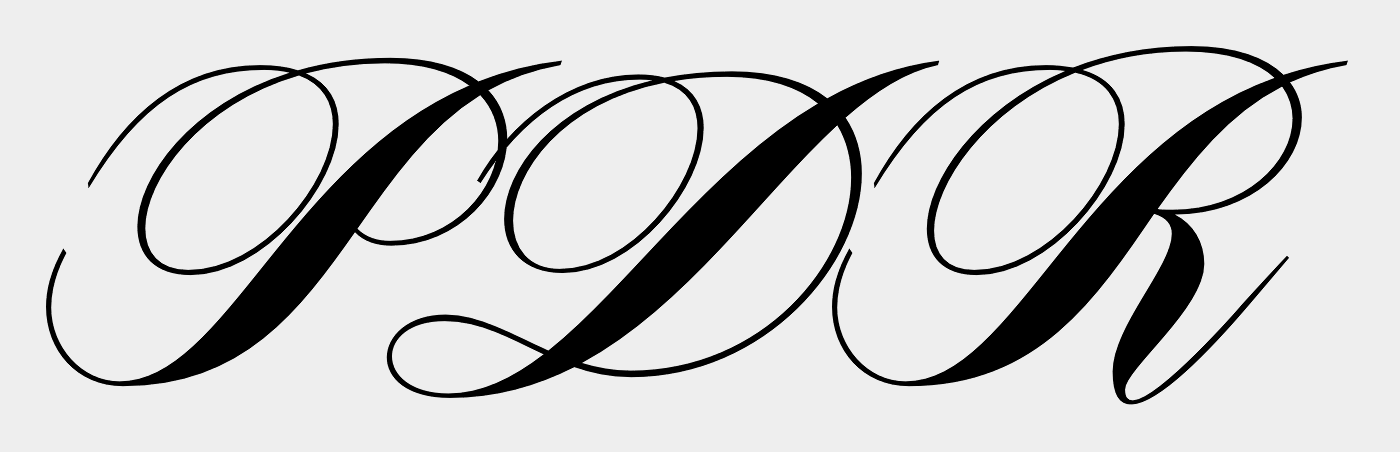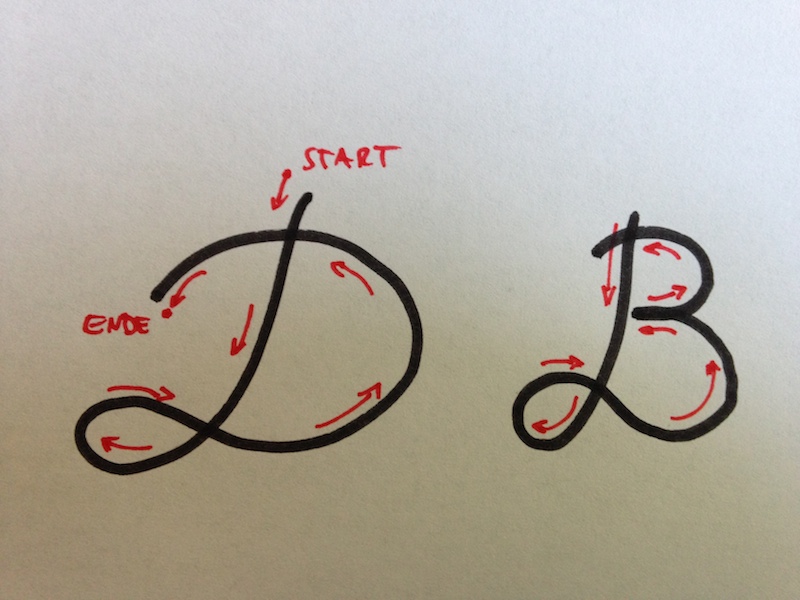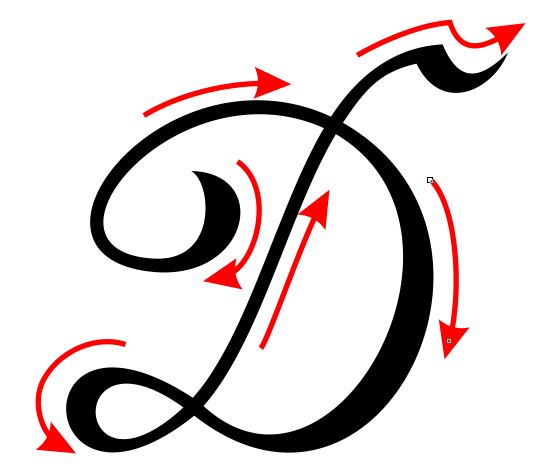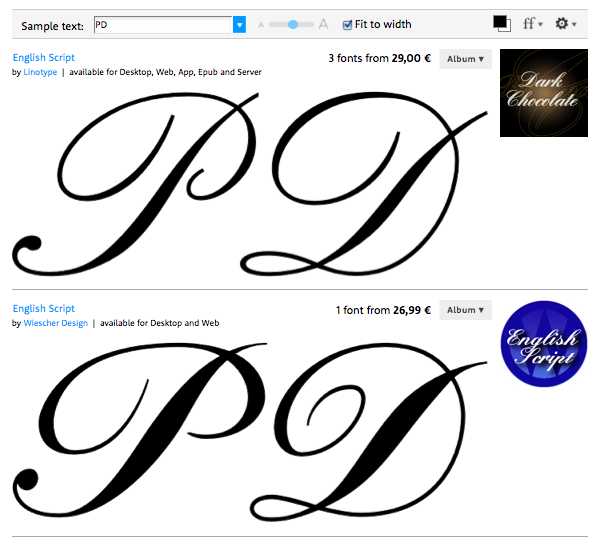
Strichstärken-Modulation des Majuskel D bei der englischen Schreibschrift
Ich vermute, dass der untere Teil des D-Bauches gemeint ist. Ich habe das gerade mal mit einer Feder auf die Schnelle ausprobiert: Bei mir entsteht da genau das gleiche Linienmuster, wie im Buchstaben D gezeigt. Wenn ich das D in einem Schwung schreibe, dann setze ich zunächst oben mit der Geraden an und ziehe die Feder nach unten. Komme ich dann zur Rundung des D, ist dies eine Aufwärtsbewegung der Feder, bei der naturgemäß keine Verdickung entstehen kann. Beim P und beim R setzt man die Feder von oben an, deswegen gibt es Verdickungen in der Linie.
Ich vermute, dass der untere Teil des D-Bauches gemeint ist. Ich habe das gerade mal mit einer Feder auf die Schnelle ausprobiert: Bei mir entsteht da genau das gleiche Linienmuster, wie im Buchstaben D gezeigt. Wenn ich das D in einem Schwung schreibe, dann setze ich zunächst oben mit der Geraden an und ziehe die Feder nach unten. Komme ich dann zur Rundung des D, ist dies eine Aufwärtsbewegung der Feder, bei der naturgemäß keine Verdickung entstehen kann.
Ja, der Bauch ist gemeint. Es liegt doch am Kalligrafen wann er Druck auf die Feder ausübt. Das geht natürlich nur bei abwärts laufenden Bewegungen, aber der Bauch ist doch abwärts. Also ich kann mit meiner Feder problemlos eine Zunahme der Strichstärke herbei führen.
Ne der Bauch geht aufwärts – also ganz im Gegensatz zum echten Leben :party:
Due beginnst oben rechts, ziehest dann runter machte unten links die kleine Schleife und dann den Bauch als Bogen gegen den Uhrzeigersinn, bis du links oben aufhörst. Anders als P und B wird das D also in eins durchgeschrieben. Mit B geht das aber auch. Hier ne schnelle Skizze, die Feder wollte ich jetzt nicht extra rauskamen ;-)
Ahhh, ich wurde total verwirrt durch meine Sign-Painting Recherchen. Da wird nämlich überraschend oft neu angesetzt. Wahnsinn, dass man das in einem Zug macht. Danke :)
Interessant: Ich habe die Buchstaben in der Grundschule so zu schreiben gelernt. Also mit weniger Zierschnörkeln natürlich und mit normalem Füller, aber die Form, in der man die Schreibbewegung ausführte (von Tobi schön illustriert), war die gleiche.
Also ich kann das nicht aus der Schule … weiß garnicht, woher ich das abgeschaut habe. Normal schreibe ich allerdings auch anders, wie „Start“ und „Ende“ zeigen :-)
Unter dem, was mir an Handschriftlichem untergekommen ist, gibt es durchaus Schreiber, die ein rechtsdrehendes D bevorzugen, das sieht dann (mal eben schnell aus dem Gedächtnis gezeichnet) etwa so aus:
Ich habe mich ja schon einiges mit Schulausgangsschriften beschäftigt, und dabei eben auch diverse Fachartikel zur Entwicklung dieser Schriften studiert, in denen die Mängel der bisher üblichen, historisch tradierten Schulschriften beleuchtet wurden. Hier insbesondere die für die kindliche Motorik problkematischen Formen der Lateinischen Ausgangsschrift, die auch mir damals nicht selten Schmerzen in der Hand verursachte, als ich im „Schreiben-lernen-Alter“ war.
Und hier wurde nicht selten dargeledt, dass für die rechte Hand eben eine kreisende linksdrehende Bewegung die natürlichere und leichter umzusetzende Form ist, Das wird wohl auch einer der gründe sein, dass sich die Mehrzahl der mit einem bogenförmigen Element geschriebenen Buchstaben eben liksdrehend geschrieben werden, und manche, die eigentlich einen rechtsdrehenden Bogen besitzen, in der späteren individuellen Handschrift eher zu liksdrehenden Formen tendieren, und damit zur Wiederaufnahme eigentlich nicht mehr gelehrter Unterscheidungszeichen, wie dem Häkchen über dem u führen, weil das n dann eben auch durch die linksdrehende Schreibung wie u geschrieben wird.
Für Linkshänder war das übrigens auch nicht ohne.  :nicken:
Davon ab: Ich habe gestern noch mal ein paar Schreibübungen in Lateinischer Ausgangsschrift gemacht – und mir ist fast die Hand abgefallen! Der Zwang, alle Buchstaben eines Wortes ohne abzusetzen aneinanderzureihen ist wirklich unnötige Quälerei. Im Laufe der Zeit entwickelt ohnehin jeder seine individuelle Handschrift, die an den Stellen, wo es zweckmäßig und angenehm ist, eben einfach neu ansetzt.
Das stimmt. Gerade dieses Schreiben des kompletten Wortes in einem Zug hat mir damals oft die Deutsch-Note versaut, da ich, wenn das eine Wort fertig war eher an das nächste Wort gegangen bin, als im gerade fertig geschriebenen Wort die i-Punkte zu setzen.
Später, wo man dann eben im Wort einfach abbricht, kann man die ja praktisch sofort setzen., So ist eine Schrift, die weder durchgängig aus einzelnen Druckbuchstaben, welches zu Stopps zwingst wo Buchstaben eigentlich aus dem Schwung heraus koppeln möchten, noch eine sklavisch Zwangsverbundene Schrift wie die LA wirklich gut, sonder eher so eine Art „Silben-Ligatur-Schrift“ bei denen sehr häufig benutzte Buchstabenverbindungen eben gekoppelt sein dürfen, anderes aber genau so gut getrennt.